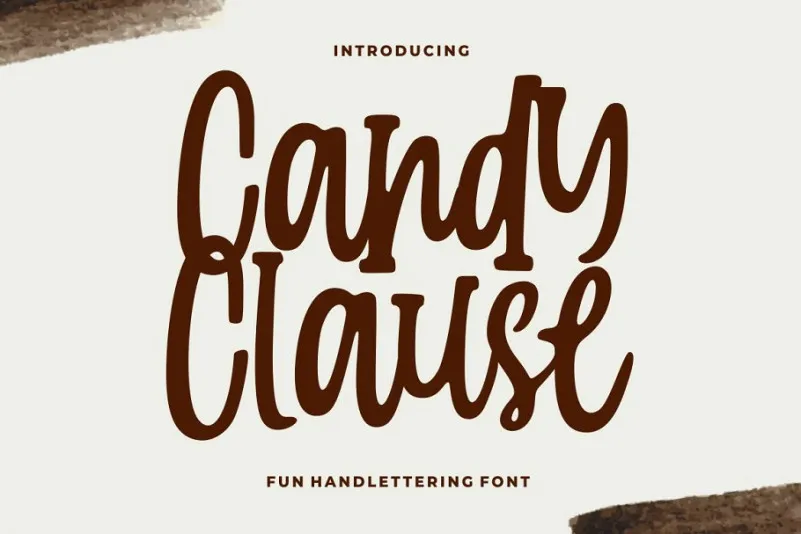
Candy Clauseis Handlettering Font
Aqui está uma descrição em português do Brasil para a página de download da fonte Candy Clauseis Handlettering Font: Introduzimos Candy Clauseis Font, uma nova fonte única e humorada projetada especialmente para quem busca personalidade nas criações digitais. Esta fonte adota um estilo ousado e fofo, repleto de carácter, firmeza e tendência atual. Ela se destaca por ser perfeitamente adaptável a diversas necessidades de design atuais. Com sua sugestão criada à mão livre em tipoface que faz parte da Candy Clauseis Font, esta opção gráfica é uma ótima escolha para anúncios, letras personalizadas, casamentos, moda e marca. O conceito se estende além dos elementos básicos de texto, incorporando letras alfabéticas completas, números e pontuação. Esta fonte atingiu o ideal perfeito para trabalhos em invitações, design gráfico, logotipos e criação de marcas. Adicionar Candy Clauseis à sua coleção pode fazer um verdadeiro diferencial em vários ambientes do design visual.